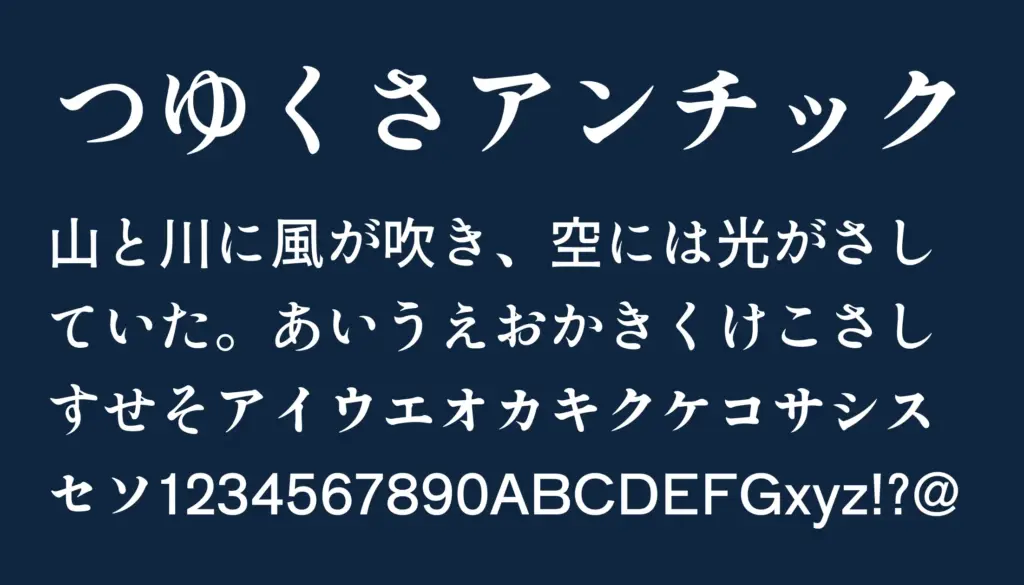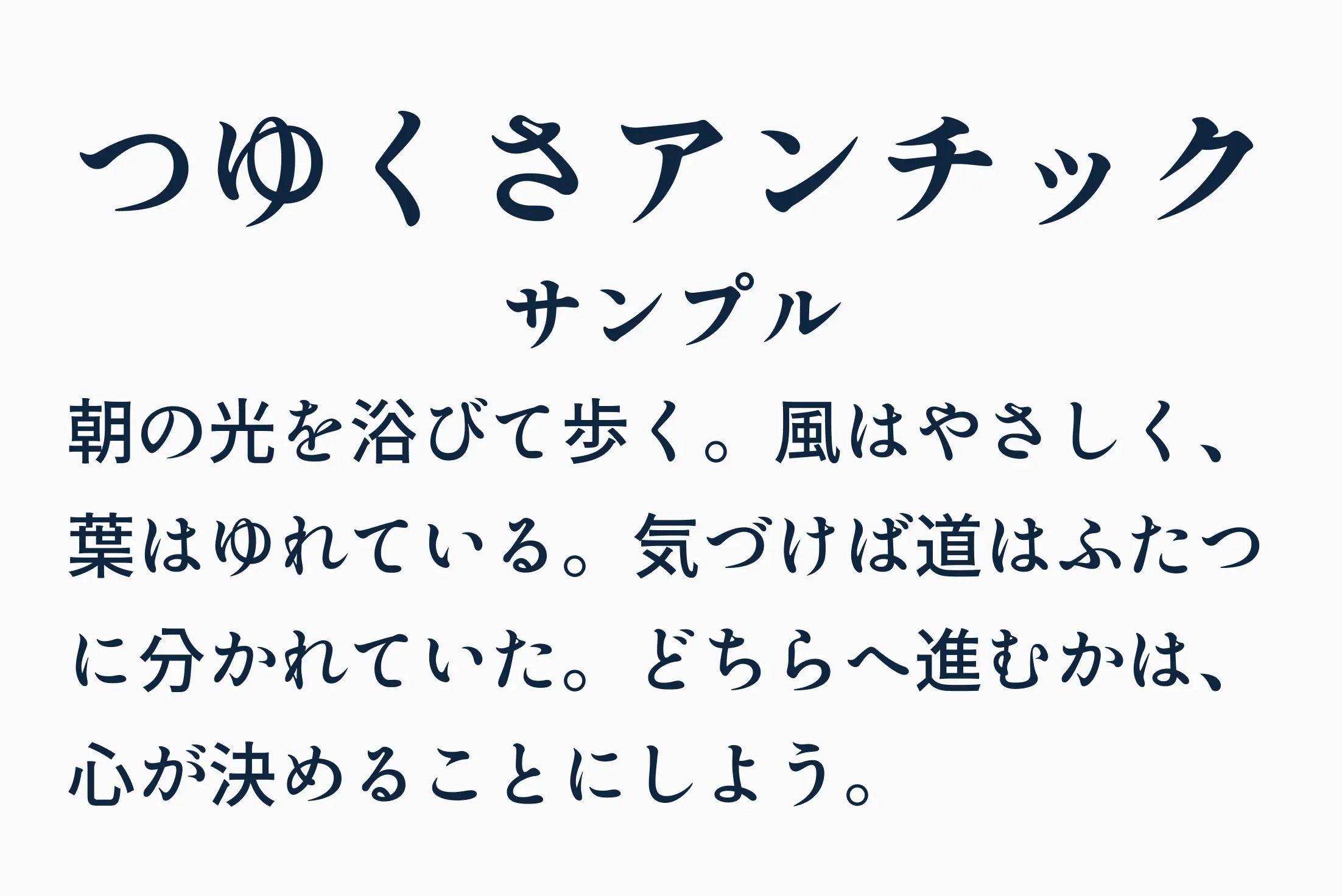
古風で情緒あるかな文字に濃いめの筆致が加わった、アンチック風フォント。濁点や半濁点がしっかり主張され、可愛さと力強さが共存する独特のビジュアルが魅力です。ハートマークや外字も収録されており、創作物・ロゴ・うちわ文字・動画字幕など幅広く使えます。昭和レトロ感のある温かみと、手書き風の優しさを併せ持つフォントです。
つゆくさアンチック